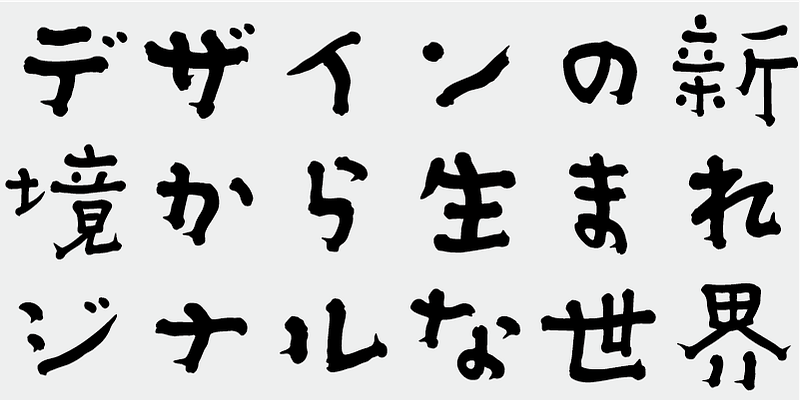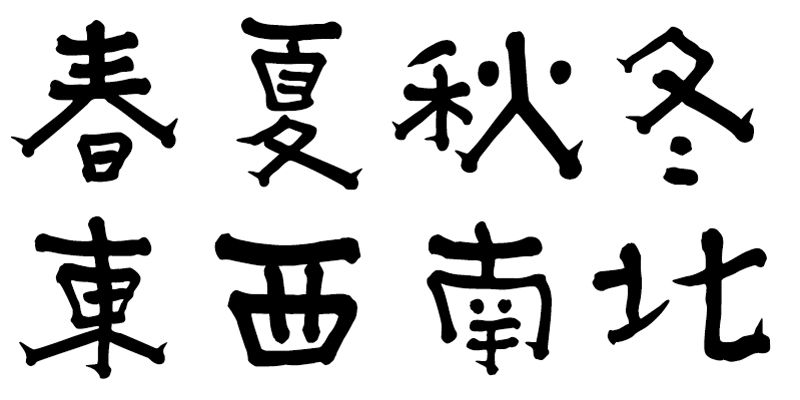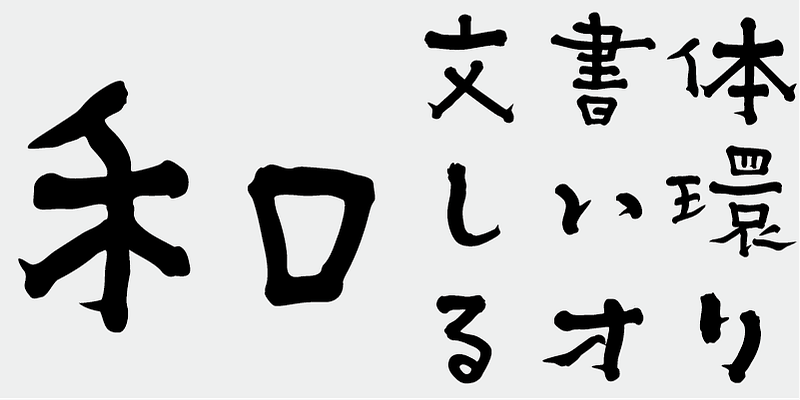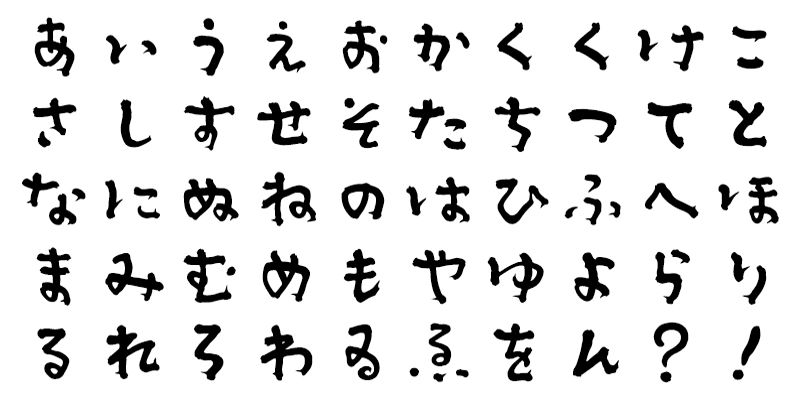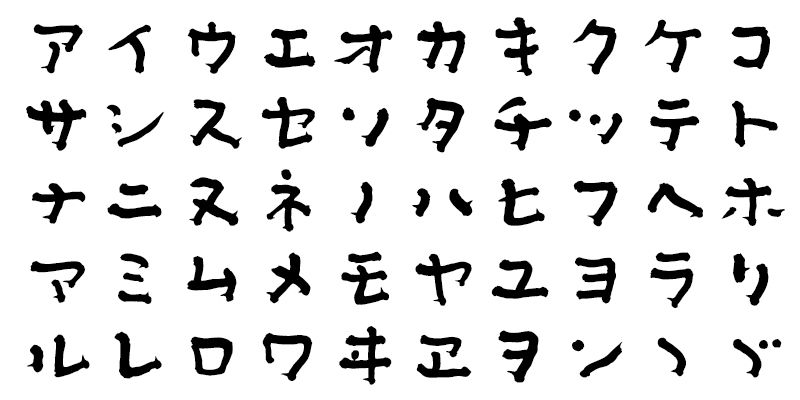
이 서체는 강하고 완고하지만 부드럽고 친절한 남자의 이미지를 연상시킵니다.
이 글꼴에는 신문사, 출판사, 언어 연구소가 만든 문자 빈도표에서 선정된 가장 많이 사용되는 간지 문자 1,000개와 더불어 206개의 가나 문자와 구두점이 포함되어 있습니다.
오늘날 일본어 글꼴 제작에서는 JIS 표준의 7,000자가 필수로 간주됩니다. 그러나 모든 글꼴에 정말 7,000자가 필요할까요? 사진 식자 시대에는 훨씬 적은 수의 문자가 필요했습니다. 독립 서체 디자이너 그룹인 FONT1000은 그 간단한 질문으로 시작했습니다. 일본어 서체에 필요한 최소 1,000자의 한자(표의 문자)를 선택했고 이를 지원하는 서체와 글꼴을 적극적으로 만들었습니다. 이 1,000자의 한자 문자 세트는 신문사, 출판사, 언어 연구 기관 등에서 수집한 문자 빈도 데이터를 사용하여 선택되었으며 가나 음절 문자 및 구두점도 포함합니다. FONT1000은 2001년에 25명의 디자이너와 25개의 서체로 시작했습니다. 현재는 130개의 서체를 보유 중이고 거의 40명의 멤버를 포함하도록 성장했으며, 더 많은 문자가 있는 글꼴 작업이 가능하게 되었습니다.